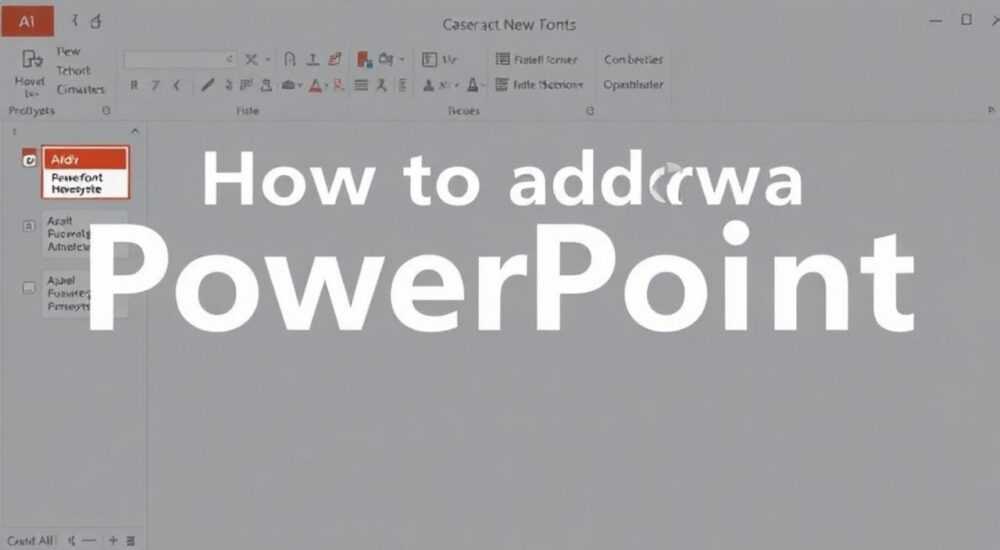
Как добавить новый шрифт в повер поинт
Создание качественных презентаций в PowerPoint требует особого внимания к деталям, где выбор шрифта играет ключевую роль в восприятии информации. Однако часто возникают ситуации, когда стандартных шрифтов программы недостаточно для реализации творческих идей или соответствия корпоративному стилю. Многие пользователи сталкиваются с проблемой отсутствия нужного начертания букв среди предустановленных вариантов, что ограничивает возможности дизайна презентации. Интересно, что решение этой задачи гораздо проще, чем может показаться на первый взгляд – достаточно всего нескольких минут, чтобы существенно расширить типографические возможности программы.
Почему важно использовать новые шрифты в PowerPoint
В современном мире презентаций использование нестандартных шрифтов становится важным инструментом визуальной коммуникации. Стандартный набор шрифтов PowerPoint, хотя и достаточно обширен, не всегда соответствует специфическим требованиям проекта. Каждый новый шрифт может кардинально изменить восприятие информации, сделать презентацию более запоминающейся и профессиональной.
Особенно это актуально при создании корпоративных материалов, где соблюдение фирменного стиля является обязательным условием. Например, крупные компании часто разрабатывают уникальные шрифты, которые становятся неотъемлемой частью их брендбука. Без возможности добавления таких шрифтов в PowerPoint выполнение корпоративных стандартов становится невозможным.
Кроме того, новые шрифты могут значительно улучшить читаемость текста и эстетическое восприятие слайдов. Современные sans-serif шрифты лучше воспринимаются на экранах, а декоративные начертания помогают выделить важную информацию. Это особенно важно при подготовке маркетинговых материалов или образовательного контента.
Работа с новыми шрифтами в PowerPoint
После успешной установки шрифтов возникает вопрос их эффективного применения в презентациях. При выборе подходящего начертания следует учитывать несколько ключевых факторов. Во-первых, размер шрифта должен соответствовать назначению презентации – для демонстрации в конференц-зале минимальный размер составляет 24 пункта, а для онлайн-презентаций желательно использовать не менее 28 пунктов.
Цветовая гамма шрифта должна гармонировать с общим дизайном слайда и обеспечивать достаточный контраст с фоном. Например, светлые шрифты хорошо читаются на темном фоне, а темные – на светлом. При этом стоит избегать слишком ярких цветов, которые могут вызывать усталость глаз у зрителей.
Важным аспектом является сочетаемость различных шрифтов между собой. Как правило, рекомендуется использовать не более двух-трех разных шрифтов в одной презентации. Хорошо работают комбинации шрифтов с разным начертанием – например, классический serif для заголовков и современный sans-serif для основного текста. Такое сочетание создает визуальную иерархию и делает презентацию более структурированной.
Альтернативные методы добавления шрифтов
Существует несколько альтернативных способов работы с нестандартными шрифтами в PowerPoint, которые могут быть полезны в различных ситуациях. Первый метод – использование облачных шрифтов через Microsoft Office Fonts. Эта функция позволяет получить доступ к расширенной библиотеке шрифтов непосредственно через интерфейс PowerPoint, без необходимости их локальной установки. Достаточно подписаться на соответствующую службу и выбрать нужный шрифт из доступных вариантов.
Второй вариант – применение векторной графики вместо текста. Этот метод особенно актуален при работе с логотипами или специфическими символами. Преобразование текста в кривые (через Adobe Illustrator или аналогичные программы) позволяет сохранить точное начертание символов независимо от установленных шрифтов на компьютере получателя презентации.